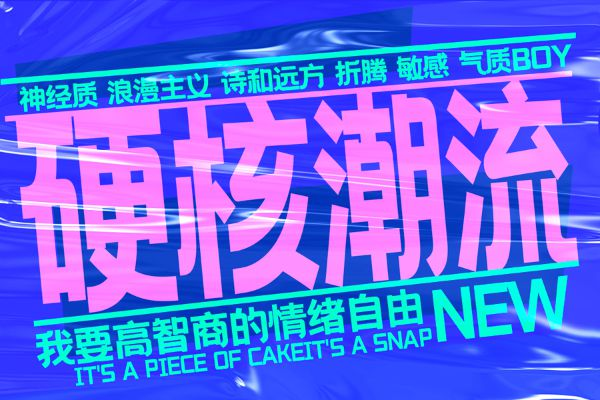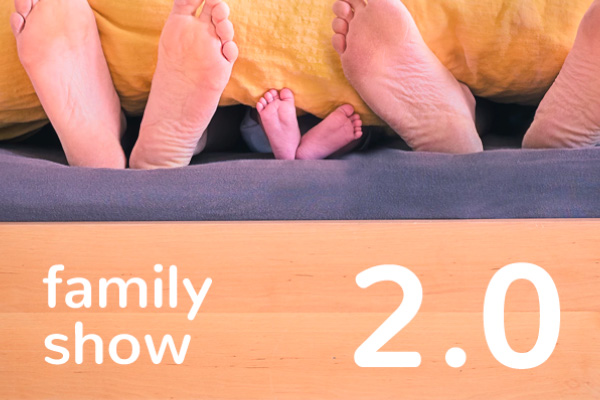
9款适合电商行业的字体推荐,新手必收藏
一个好的字体能让标题突出重点、让描述易读,让价格一目了然。相反,如果字体选择不当,比如用了过于花哨的或不兼容的样式,就会让页面看起来混乱,用户在手机或电脑上阅读时会感到吃力,最终导致商品详情页转化率下降。
本文我会详细介绍我用过并推荐的9款适合电商行业的字体。这些字体大多是免费商用或易于使用的,我会尽量提供实用建议,让你能直接应用到你的店铺中。
字由文艺黑属于简约厚重的黑体字,笔画粗细均匀有力,字形方正适中,摒弃传统黑体的生硬厚重,增添柔和文艺质感。字重适中醒目,阅读舒适度高,繁简字符齐全,适配书籍标题、文艺海报、文创封面、品牌标语等场景。
思源黑体
思源黑体是Adobe和Google联合推出的开源字体系列,有多种粗细,从ExtraLight到Heavy都能满足需求。它的笔触简单、中宫宽阔、整体均衡,看起来既现代又稳重,没有任何多余的装饰。风格特点是字面率高,阅读时眼睛疲劳感低,适合各种屏幕显示。
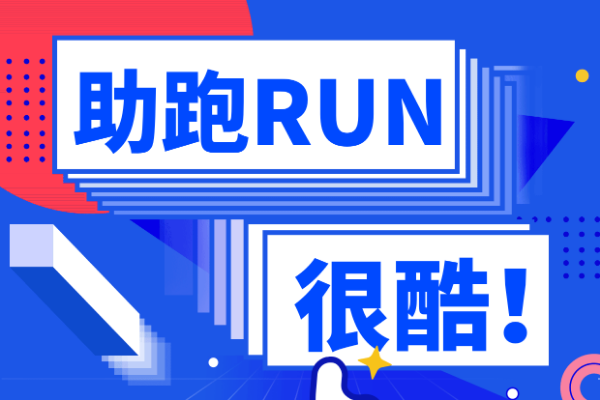
Nunito
Nunito是平衡良好的圆头无衬线字体,笔划柔和圆滑,转角处也很舒服。风格特点是结构饱满、亲和力强,看起来不像冷冰冰的科技风,而是温暖且友好。整体给人一种现代生活感,不突兀。
我用它来做电商的促销标题和活动页面的主标题。在一次户外用品店铺的项目中,我把Nunito用在“限时折扣”这类文案上,结果用户点击率提高了不少。
Lora
Lora是现代感衬线字体,有一点非衬线字体的影子,相对宽松清晰。风格特点是适中的对比度,适合电子屏幕展示,也能用于印刷品。
在电商中,我主要用Lora做正文内容和产品描述。理由是它在屏幕上显示很清晰,衬线细节不会破坏阅读流畅性。比起纯无衬线字体,Lora能让长段落看起来更有层次感。
Inter
Inter是由Rasmus Andersson设计的免费商用字体,线条干净、风格现代,完美对称。小写混合文本的可读性特别强。风格特点是易读性高,每个字母都平衡。
我把它作为电商网站的默认字体用在标题和正文中,因为它是为用户界面专门设计的,在各种屏幕上都保持优秀阅读体验。在我的多个项目里,Inter取代了其他字体后,用户反馈页面更顺畅。
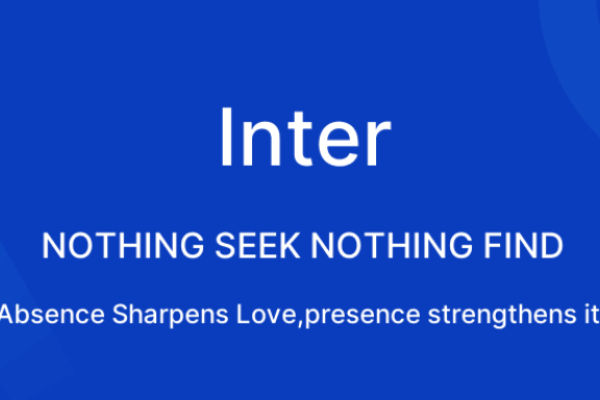
Poppins
Poppins是笔画正规、粗黑大方的英文免费字体。风格特点是整体效果大方得体,适合名片、宣传海报等。
Poppins的粗黑明了,在促销活动页用它做主标题时,视觉冲击力强但不乱。实际应用中,我发现它支持多种语言,适合国际电商。
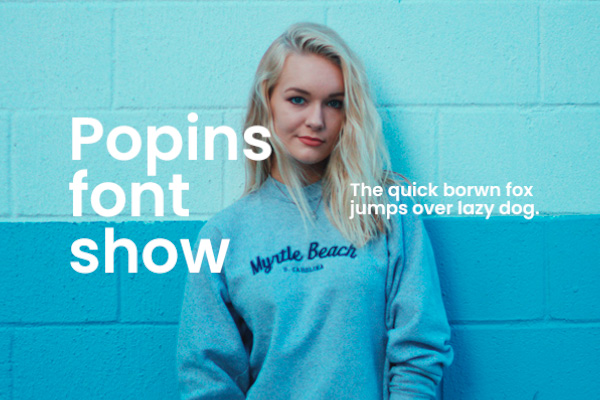
Raleway
Raleway是优雅的几何无衬线字体,笔画纤细、重量中等、宽度半伸展。风格特点是个性化、创意强。
Raleway的纤细笔画在手机端显示优雅,适合需要“精致”调性的店铺,比如美容或精品服饰。实际测试时,它在短语中特别好看。Raleway支持大量语言,在全球电商中很实用。搭配其他字体时,能让页面更有层次。
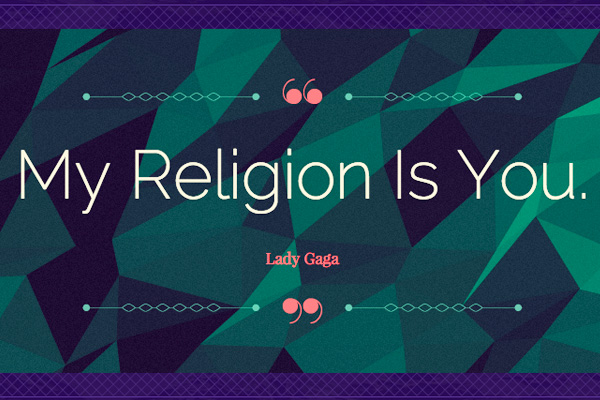
Roboto
Roboto是为Android设计的无衬线免费商用字体,圆润清晰,现代平易近人。风格特点是情绪化设计,引领干净几何哲学。
Roboto在电商详情页的导航中特别好用,因为它兼容性强。比起其他字体,它更“亲切”,适合大众消费品店铺。免费多重使用,让我能在不同项目中灵活调整。
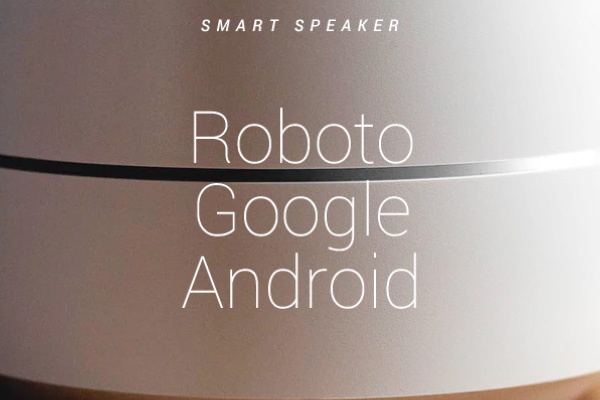
Manrope
Manrope是现代几何无衬线字体,有7种样式。风格特点是半浓缩、半圆形、半美学,极具个性。Manrope的个性设计在标题中能突出品牌特色。在我的项目中,用它做主标题时,用户反馈专业又有趣。